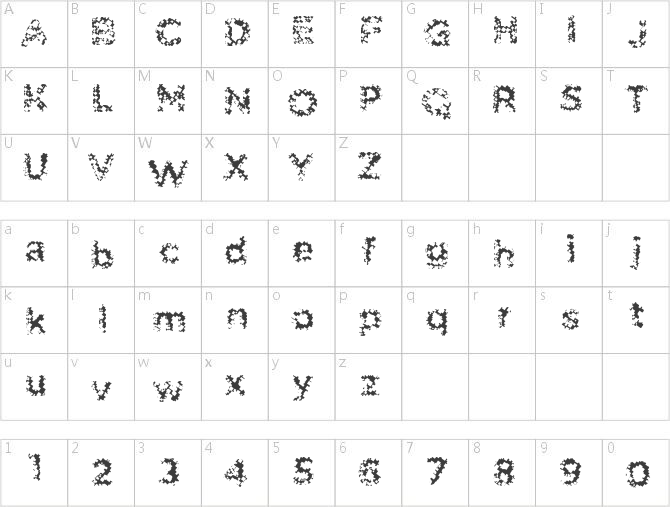
字體名稱: Pabello
Pabellona-C-Triplex
Pabellona-C-Triplex字體字庫是一款讓人賞心悅目、百看不厭的英文字體,適合各類廣告和產(chǎn)品包裝設(shè)計(jì)應(yīng)用,字體大小0.16MB,格式為ttf字體,上傳用戶是gagilang,作者/版權(quán)方為未知